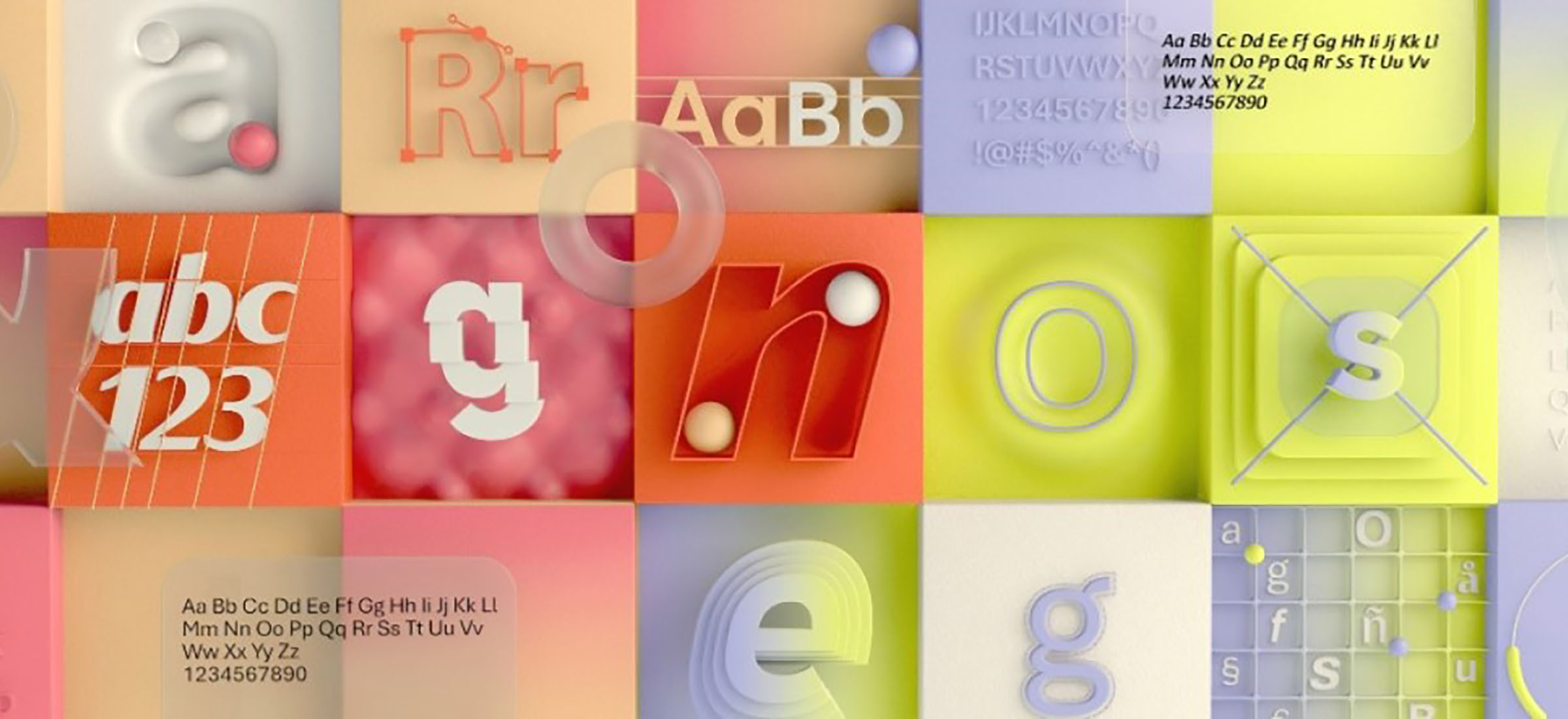
Microsoft prosi użytkowników o pomoc. Pytanie jest proste: czym chcesz pisać?
Ostatnia taka zmiana miała miejsce w 2007 r., kiedy domyślny Times New Roman został zastąpiony przez Calibri. Dziś dowiadujemy się, że i Calibri odejdzie do annałów historii. Microsoft ma aż pięć propozycji.
Prawdopodobnie każdy użytkownik Microsoft Office wie dokładnie, jak wygląda czcionka Calibri. Ta jest wybierana jako domyślna przy tworzeniu każdego nowego dokumentu tekstowego, arkusza kalkulacyjnego, prezentacji bądź innych materiałów biurowych. Microsoft uważa jednak, że ta – jak niegdyś Times New Roman – już się znudziła użytkownikom. Czas na nową.
Calibri oczywiście pozostanie jako jedna z czcionek do wyboru. Domyślną ma być jednak jedna z pięciu proponowanych przez Microsoft. Twórcy Office’a wybrali czcionki o nazwach Tenorite, Bierstadt, Skeena, Seaford i Grandview. Czemu aż pięć?
To użytkownicy Microsoft Office mają wybrać następcę Calibri – domyślną czcionkę w Word, Excel, PowerPoint i reszcie.
Microsoft prosi użytkowników o wyrażanie swoich opinii w mediach społecznościowych, najlepiej adresując oficjalny profil firmy (linkowany powyżej). Firma przy tym nie precyzuje, jak dokładnie informacje od użytkowników mają wpłynąć na końcową decyzję. Liczy się liczba głosów? Coś innego? Nie wiemy.